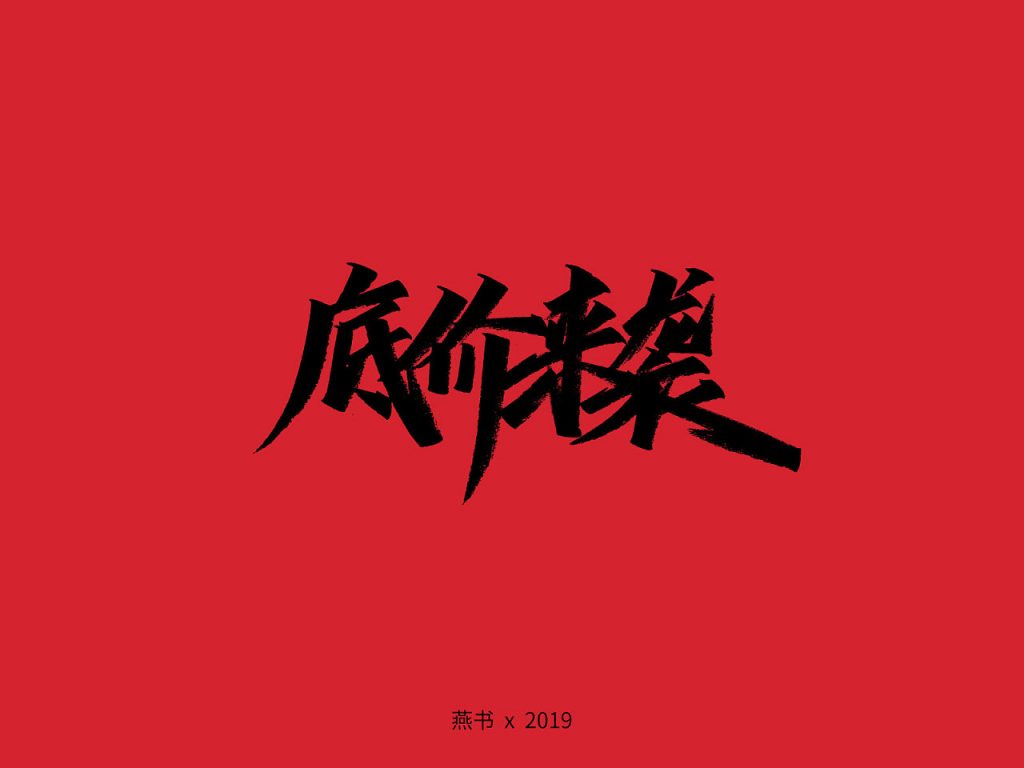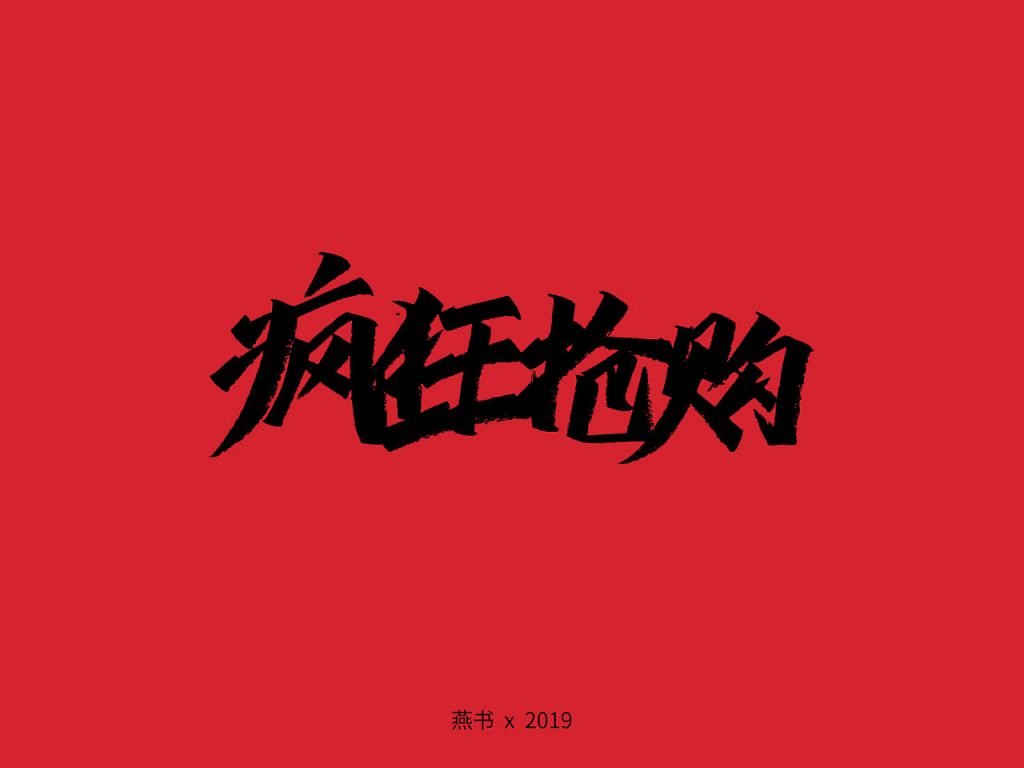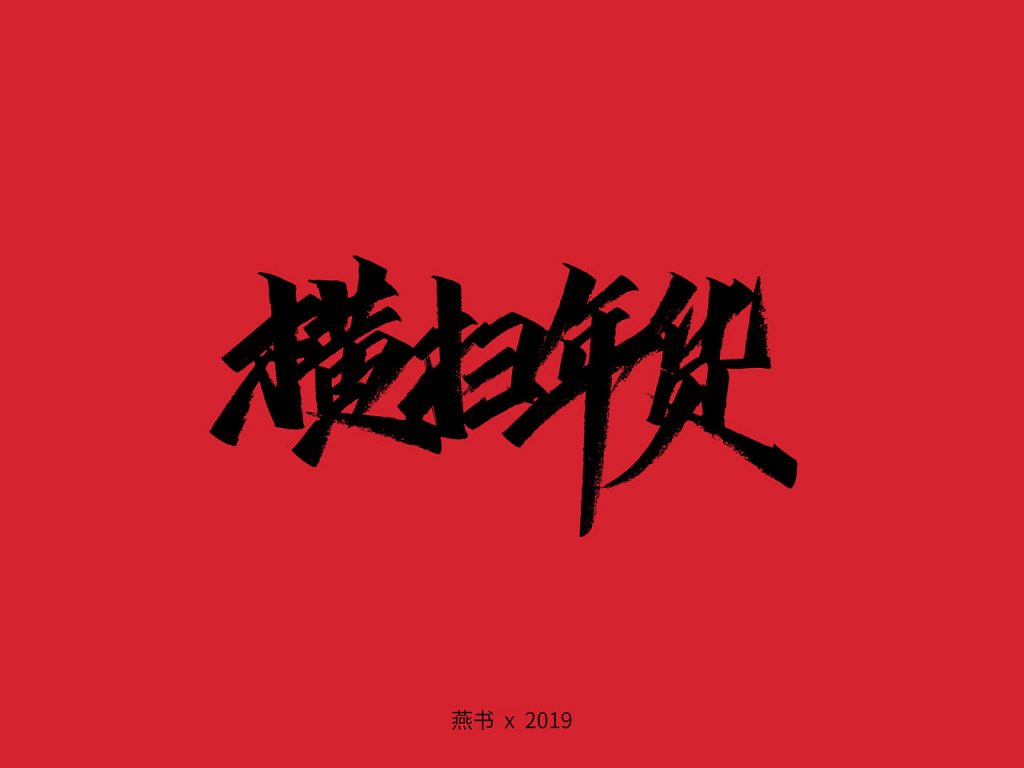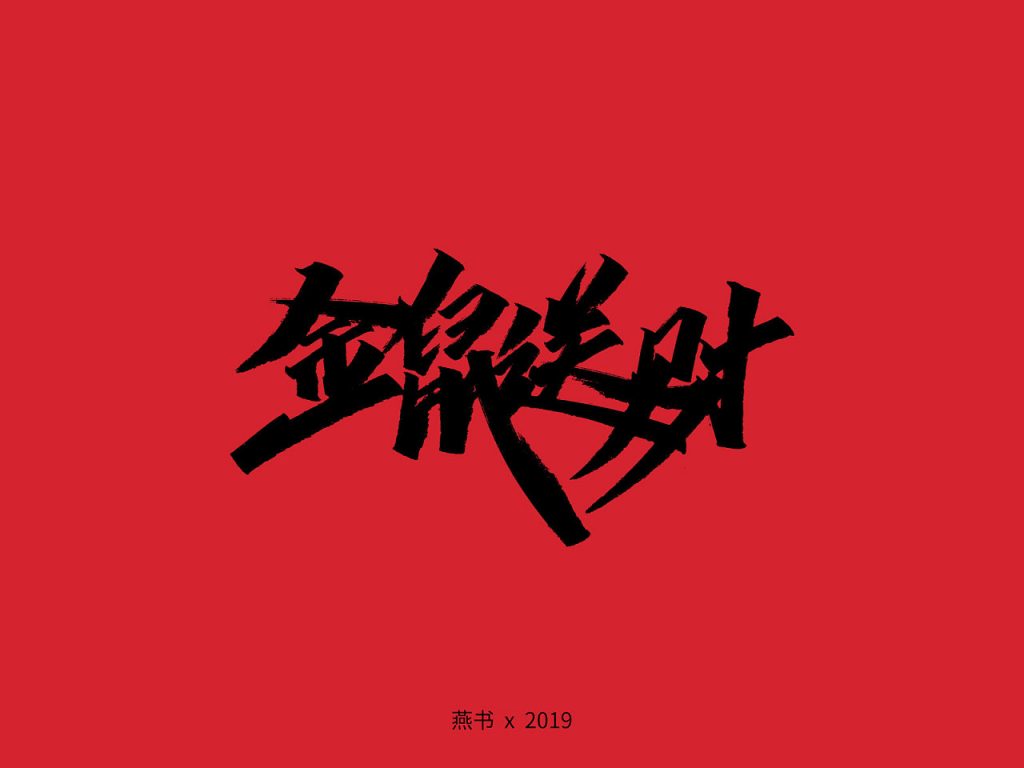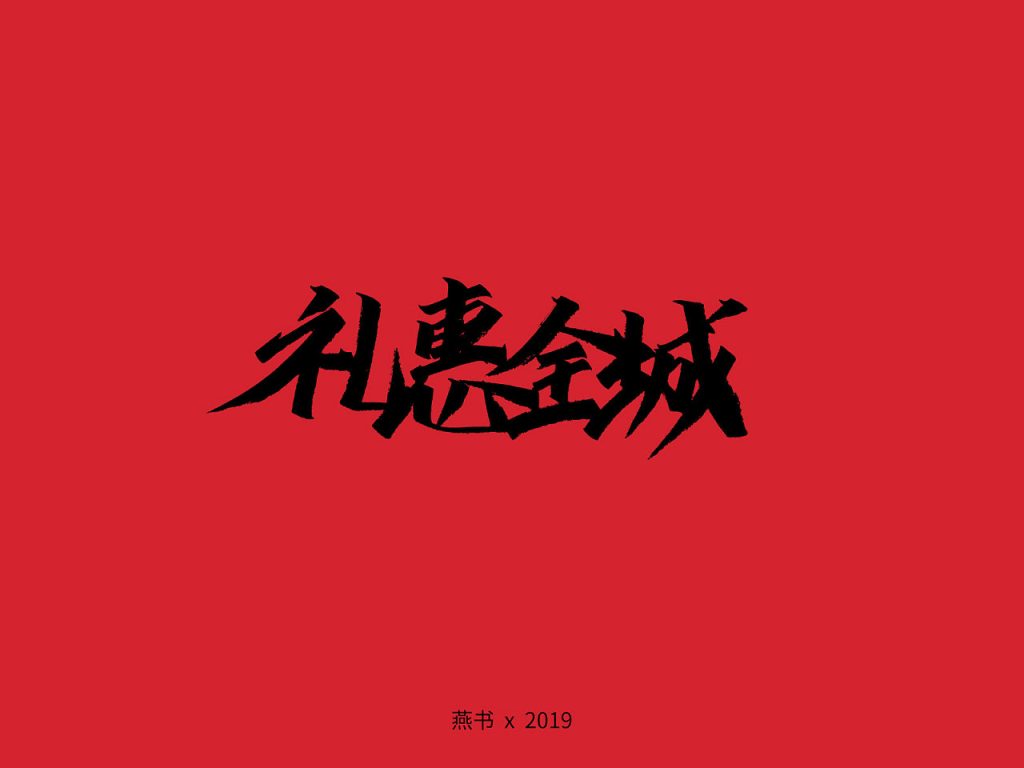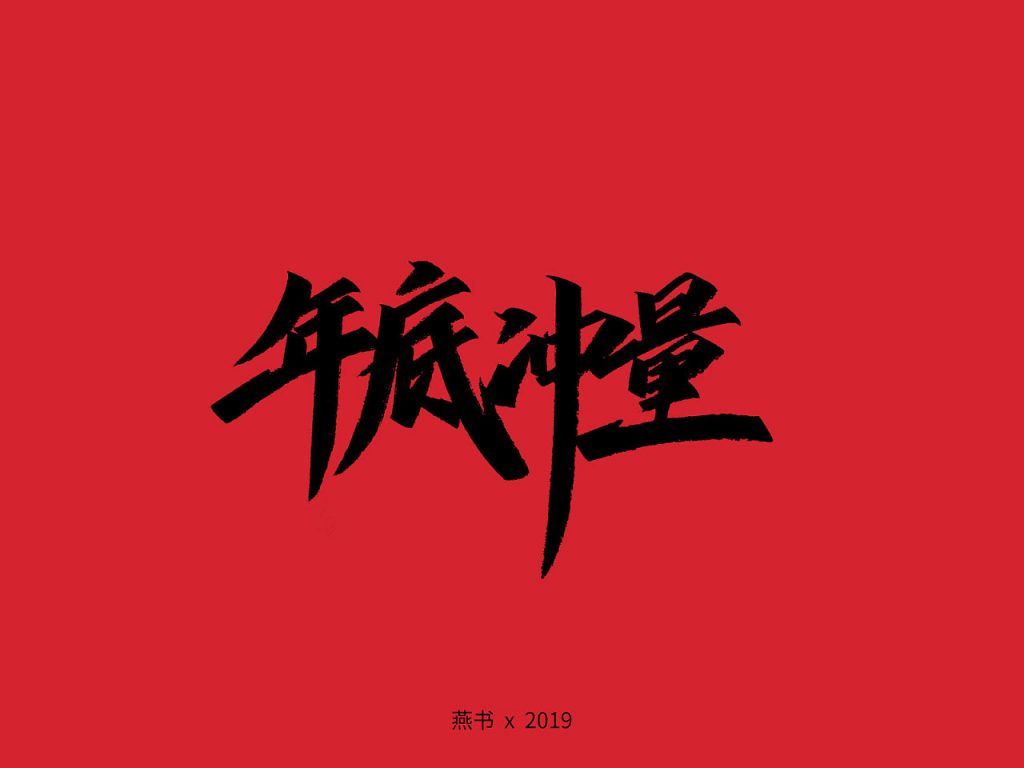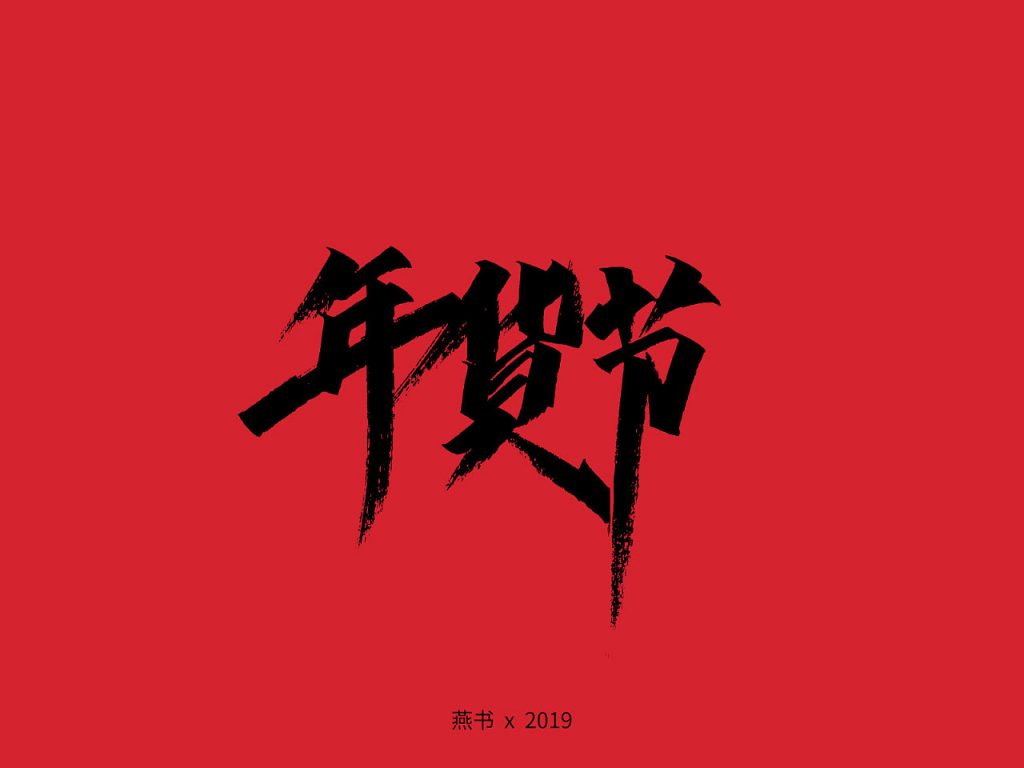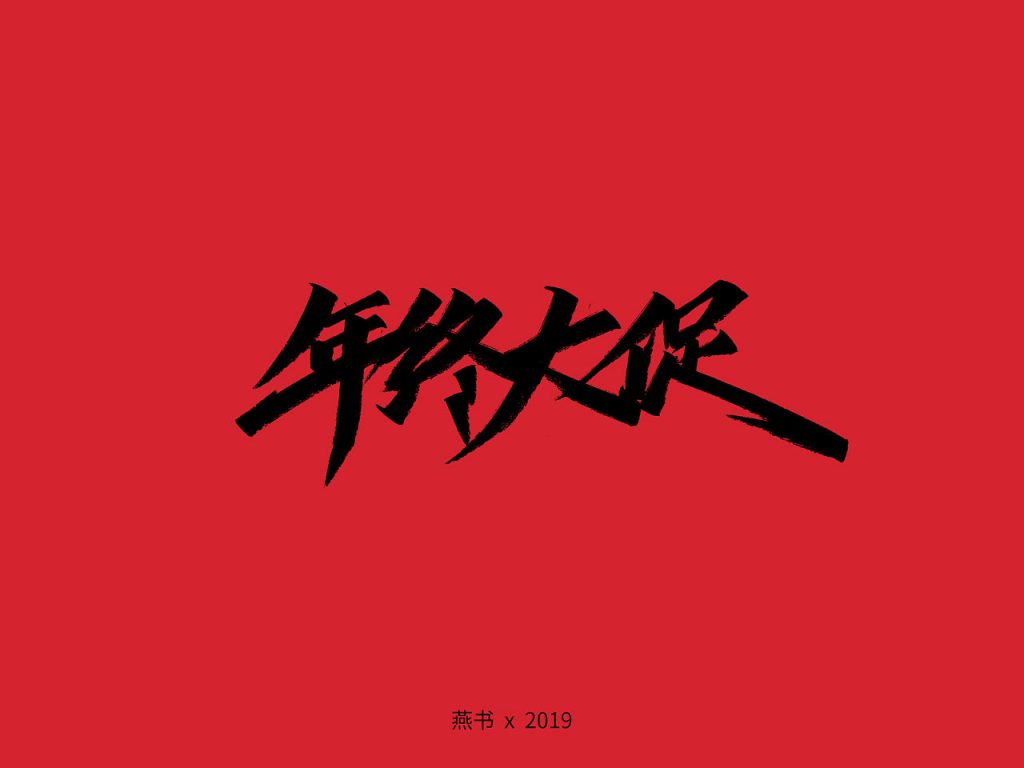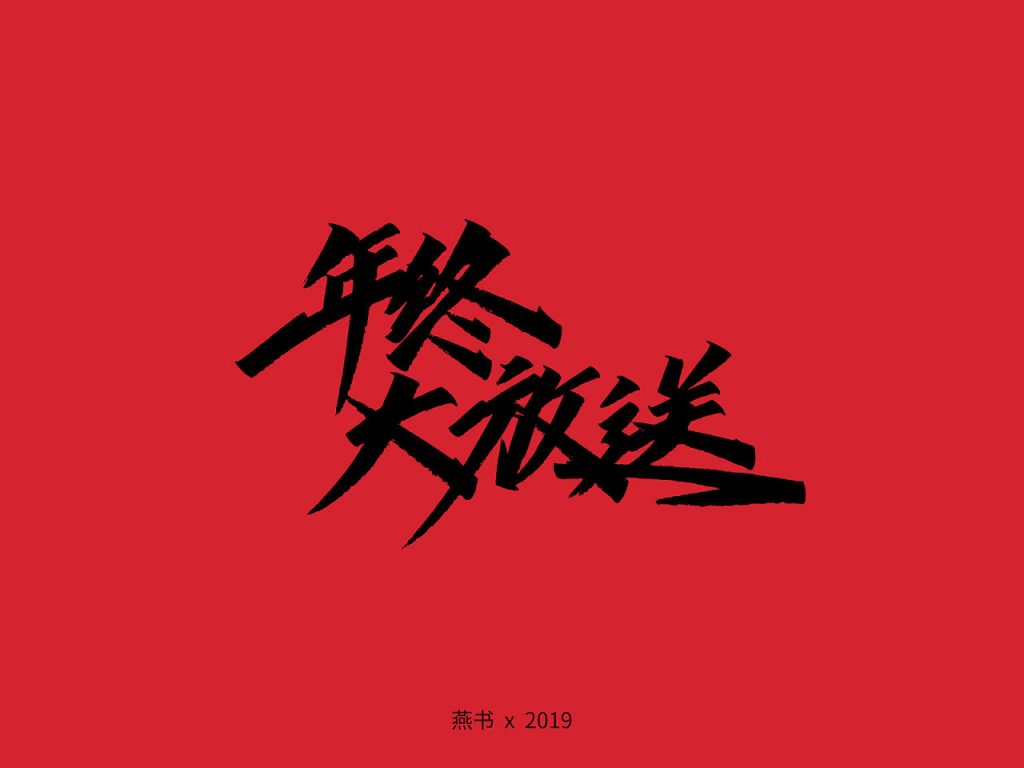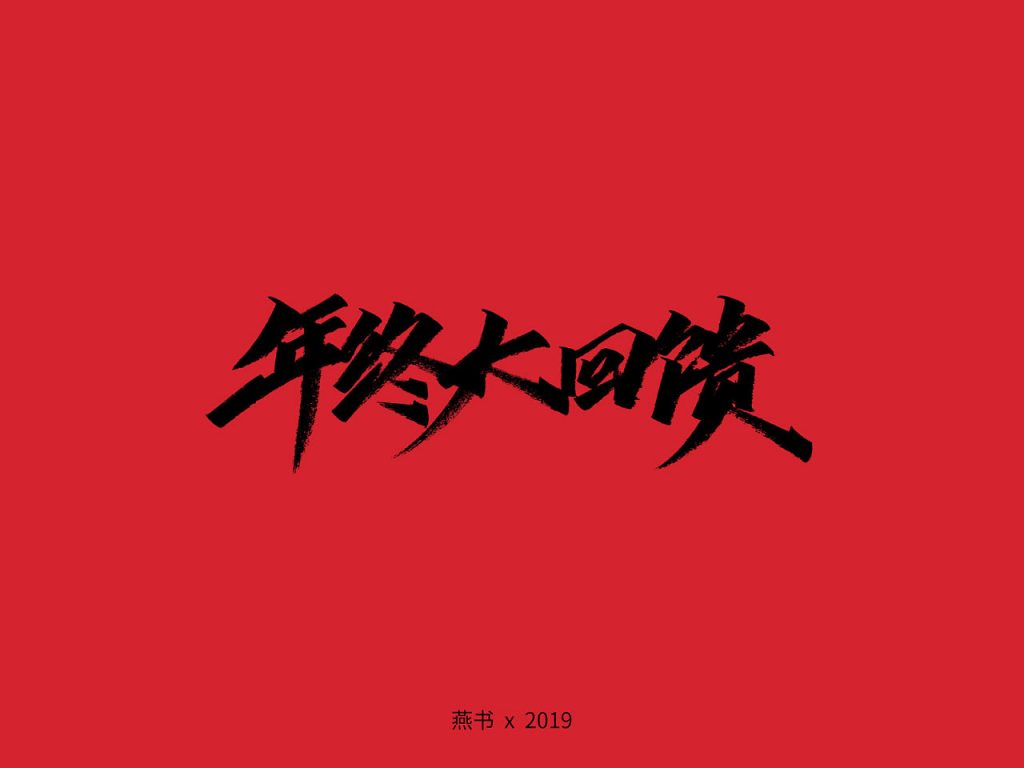
年关将近,也是设计师们最忙碌的日子了。特别是电商设计师,现在的什么节什么节太多了,几乎每天都赶活动专题。人家说程序员头秃的比较快,我觉得还是咱们设计师秃得更多。且不说一天100张图能不能做出来,甲方要五彩斑澜的黑,字体要放大的同时缩小一点,字体要高端大气上档次就能要了你的头发。
我国设计师燕书(站酷ID: 燕书 )特地来拯救大家的头发,写几27款十分漂亮的手写字体送给大家,而且是免费商用的哦! 对于写字手残的你是不是十分惊喜啊?还不赶紧下载收藏起来~~如果可以的话,去请作者喝杯咖啡或者冰阔乐吧!